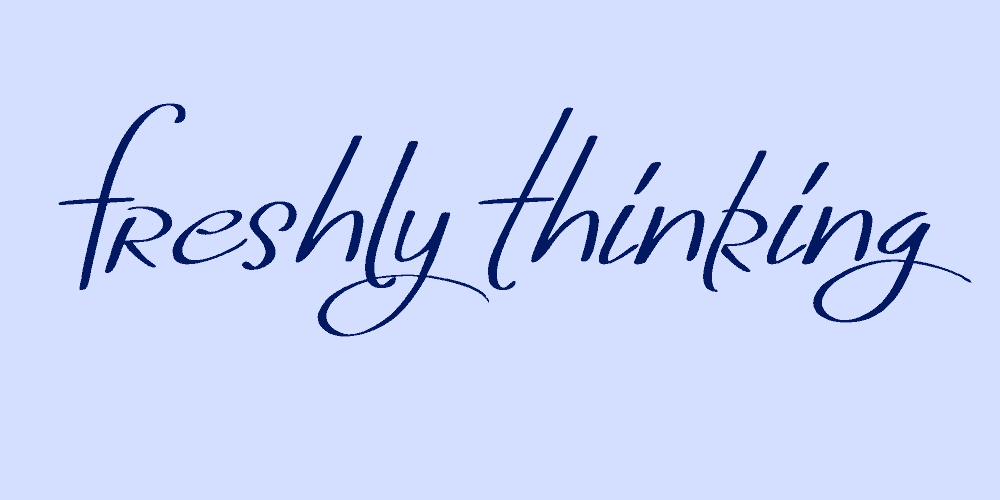
A Freshly Thinking Font é uma fonte escrita a mão criada pelo designer Hamilton que captura o espírito da natureza vibrante do Brasil. Suas letras fluidas e expressivas evocam sentimentos de descontração, criatividade e naturalismo – elementos essenciais para o cotidiano brasileiro, marcado por ricas culturas, paisagens únicas e uma conexão quase mágica com a natureza. Esta fonte é perfeita para designers que valorizam um toque pessoal em seus projetos digitais, seja na criação de logos, arte digital ou editoriais gráficos. Com sua aparência elegante e seu caráter descontraído, ela oferece uma maneira inovadora de expressar a identidade do Brasil no mundo da comunicação visual.